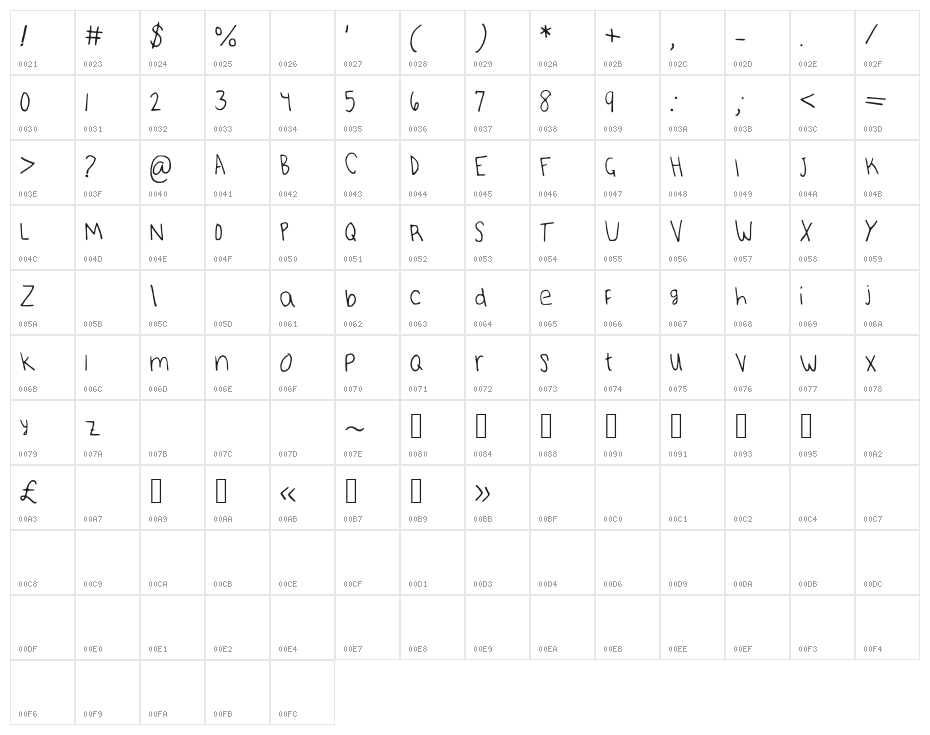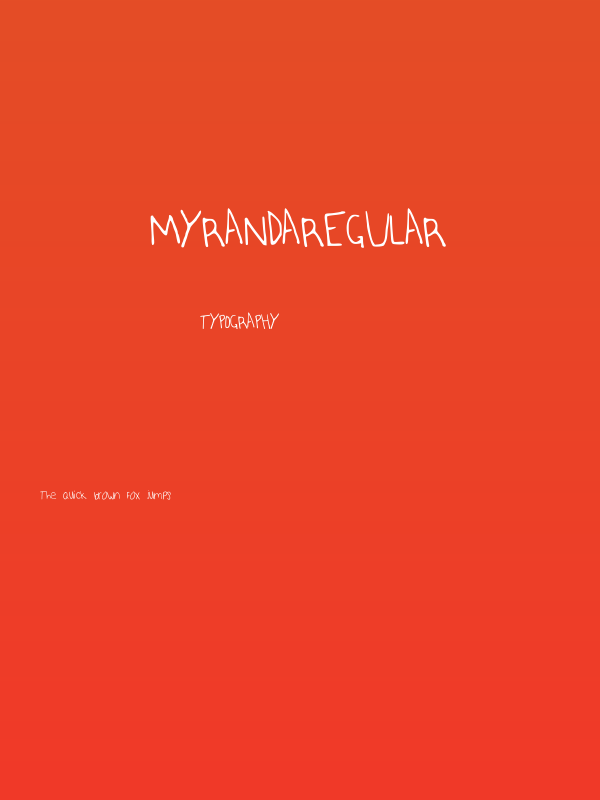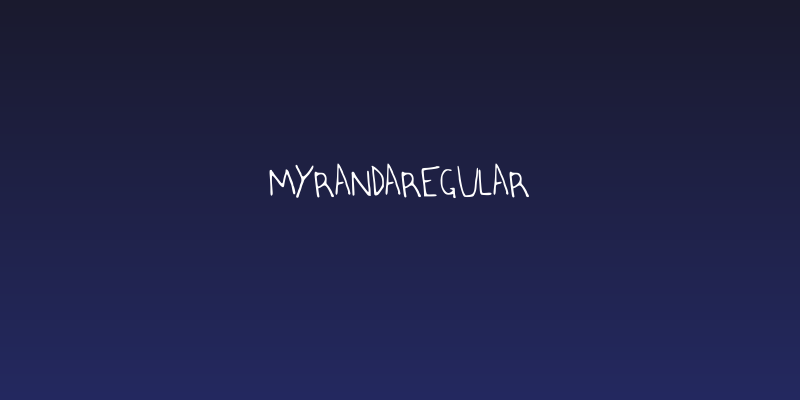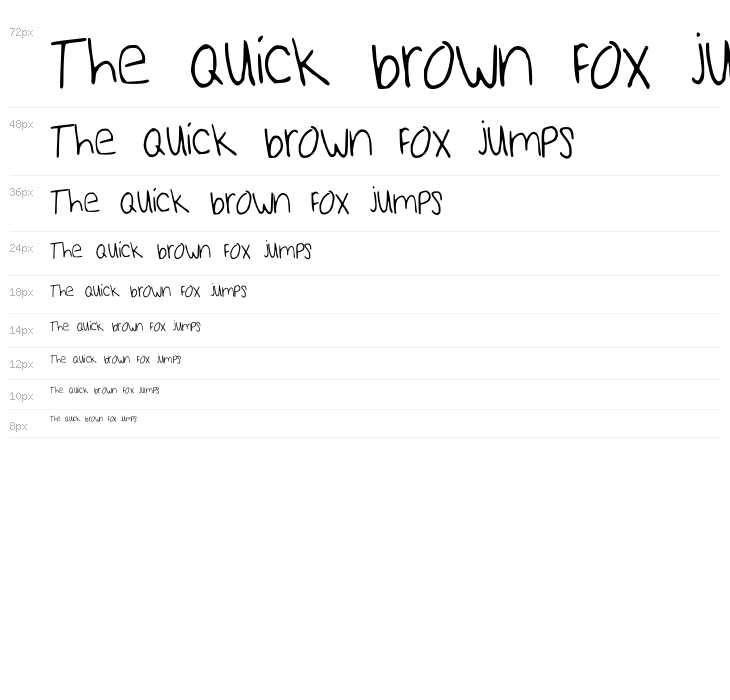
MyRandaRegular Font
| Stile generale | Casual, Whimsical |
| Caso d'uso | Headlines, Informal text, Creative projects |
| Progetti proposti | Ideal for greeting cards, children's books, personal blogs, and creative branding projects. |